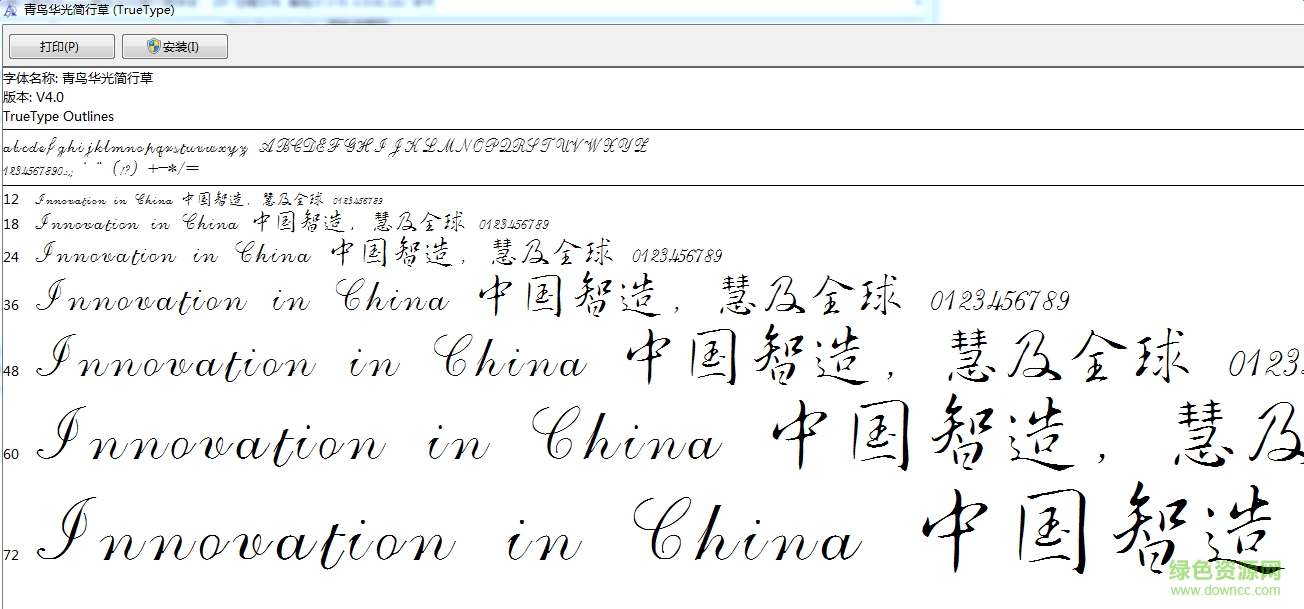
青鳥(niǎo)華光簡(jiǎn)行草
青鳥(niǎo)華光簡(jiǎn)行草字體是一款時(shí)尚草書(shū)風(fēng)格字體軟件,行草體筆畫(huà)看似隨意卻不失工整,整體效果比較酷炫養(yǎng)眼,十分耐看,深受廣大年輕人喜愛(ài),還有更多好看字體歡迎到綠色資源網(wǎng)下載使用!
字體介紹